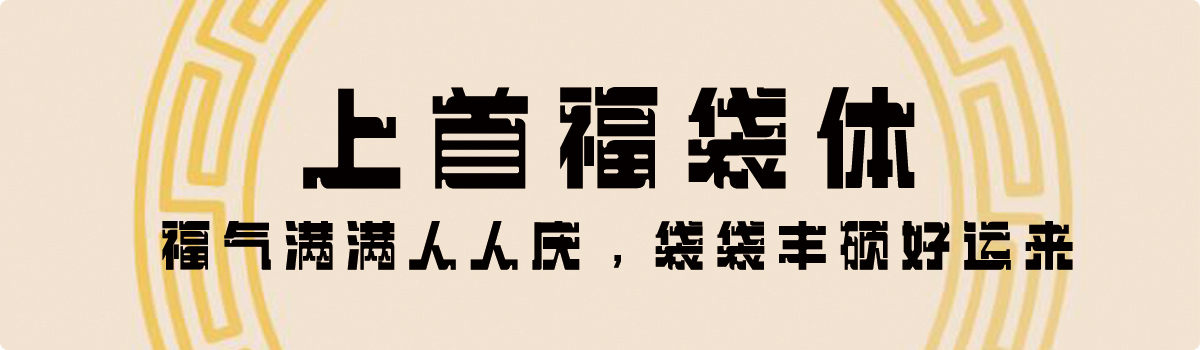
上首福袋体
上首福袋体,这款字体结构工整、笔画清晰,兼顾美观与易读性,适用于标题、正文、海报、包装、LOGO 等多种场景。字形优雅稳定,风格百搭耐看,适配日常排版与创意设计,让文字呈现更舒适、更具质感。上首福袋体一笔一画,皆是细节,以均衡的比例、流畅的线条打造舒适视觉体验,字形端正大气,风格简约现代。无论是商业设计、品牌宣传还是日常排版,都能轻松驾驭,让文字更有格调与力量。上首福袋体字体下载。